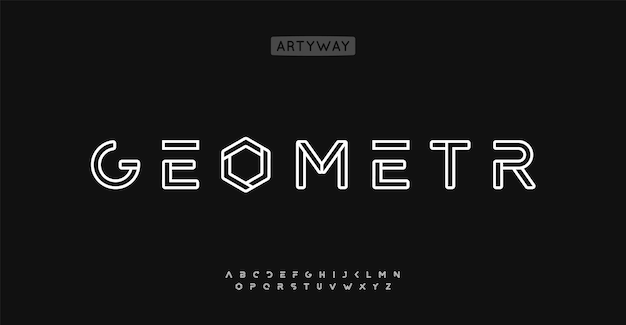
Alphabet géométrique délimité polices technologiques modulaires polices wireframe polices modernes style blueprint typographie futuriste conception typographique modulaire et structurelle polyvalente jeu de caractères vectoriel